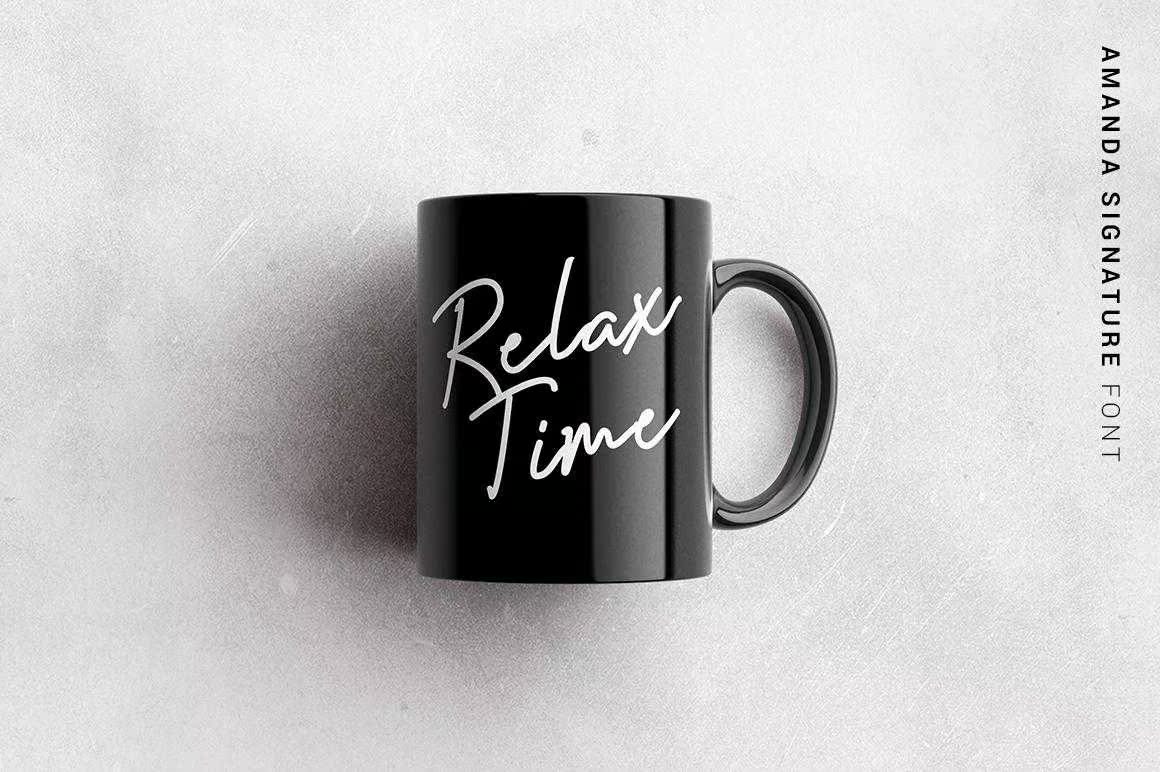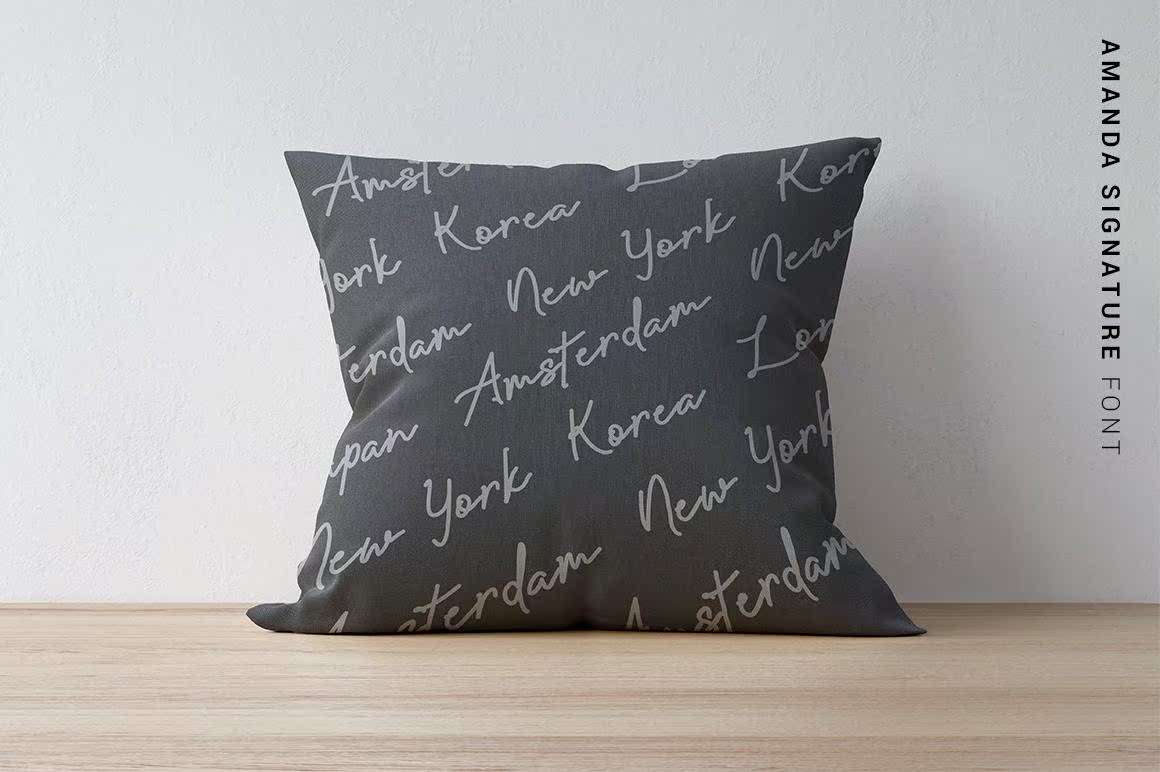
AmandaSignatures A和Write Tensignature描述了自然和风格流程。这一系列的脚本非常适合个人品牌。它的目的是让摄影师为他们的摄影业务做一个标记,即“肖像”。但是,此工作适用于所有应用。从个人品牌推广和婚礼宣传到广告宣传的所有内容都可以从本签名集中受益。Amanda签名集和书写时签名集描述了自然和样式流。本签名集是个人品牌推广的完美之作。它旨在让摄影师看到其摄影业务的标记s–其名称为“肖像”。但是,这项工作适用于所有应用。从个人品牌和婚礼宣传到广告宣传,一切都可以从这一系列签名中获益。